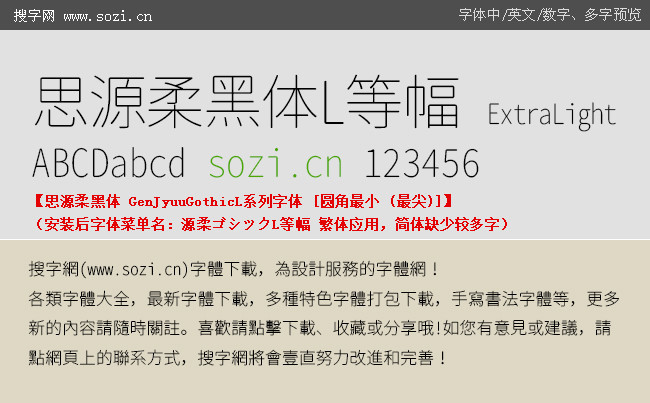
思源柔黑體L等幅-ExtraLight
搜字網(wǎng)給大家提供一款思源柔黑體L等幅-ExtraLight中文字體下載,思源柔黑體由思源黑體改造而來(lái),由日本作者自家製フォント工房制作,所以部分簡(jiǎn)體中文可能會(huì)不顯示,字柔黑承襲了「思源黑體」原有的優(yōu)雅,在文字邊角以圓邊進(jìn)行處理,相比原來(lái)思源黑體更加柔和,似黑似圓,介于二者之間,而L系列圓角最小 (最尖)。適用于大標(biāo)題、包裝設(shè)計(jì)、海報(bào)設(shè)計(jì)等應(yīng)用。